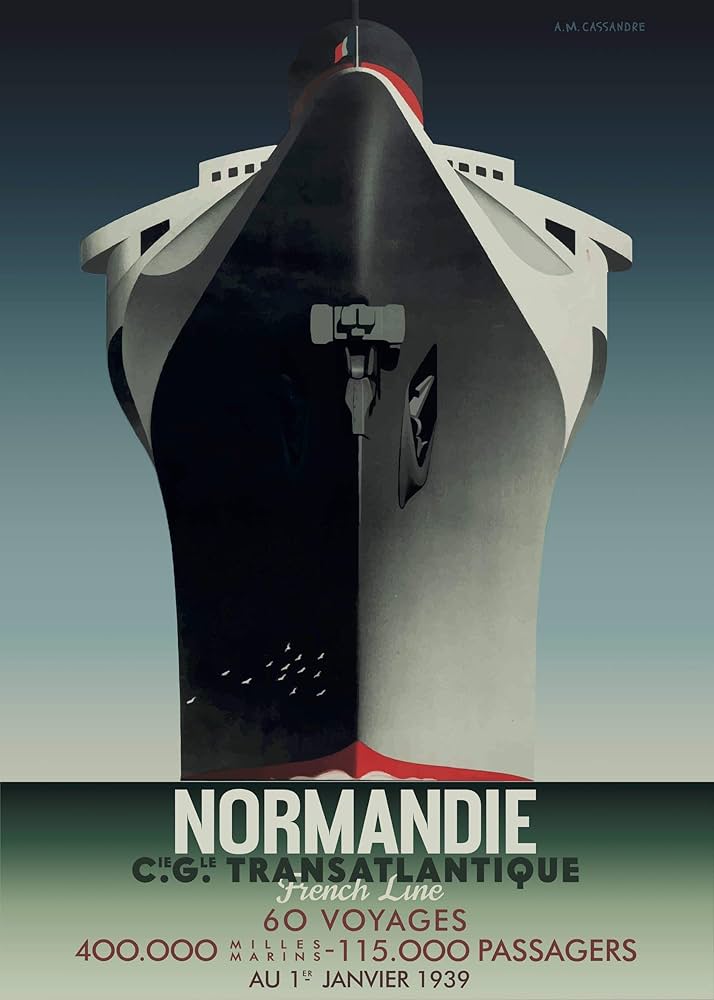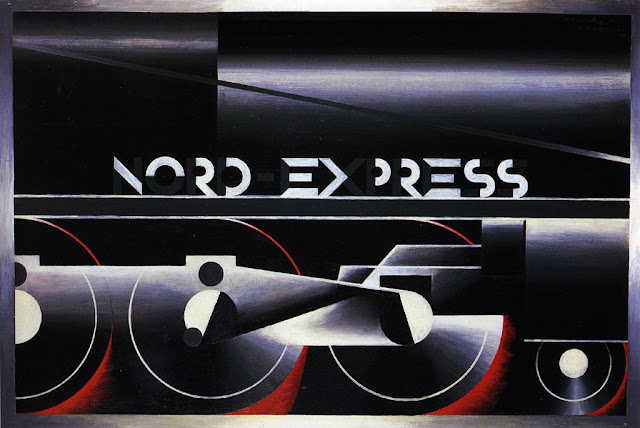
A. M. Cassandre (1901-1968)Pseudónimo de Adolphe Jean-Marie Mouron. Destacou-se na produção de posters para publicidade, principalmente com motivos ligados às viagens, que estavam em moda no período do Art Deco.Cassandre Adolphe Mouron Cassandre (24 de Janeiro, 1901 - 17 de Junho, 1968) era o pseudonimo de Adolphe Jean-Marie Mouron, um franco-ucraniano pintor, criador de cartazes e designer de fontes tipográficas. Cassandre destacou-se na produção de cartazes de publicidade, sobretudo ligada às viagens de comboio e paquetes de luxo, que estavam na moda no período do Art Deco. Os seus trabalhos obtiveram grande sucesso e tiveram influência sobre os artistas da época. O seu estilo de desenho é elegante, apresentando abstração geométrica, vastos planos de cores, as imagens em perfeita integração com as palavras. Acreditava no cartaz como meio de comunicação, capaz de passar a mensagem desejada. Tinha paixão pelas letras, segundo ele elemento fundamental do seu trabalho. Cassandre criou três fontes tipográficas:
As letras por ele desenhadas à mão em seus posters quase não podem ser distinguidas das letras tipografadas.